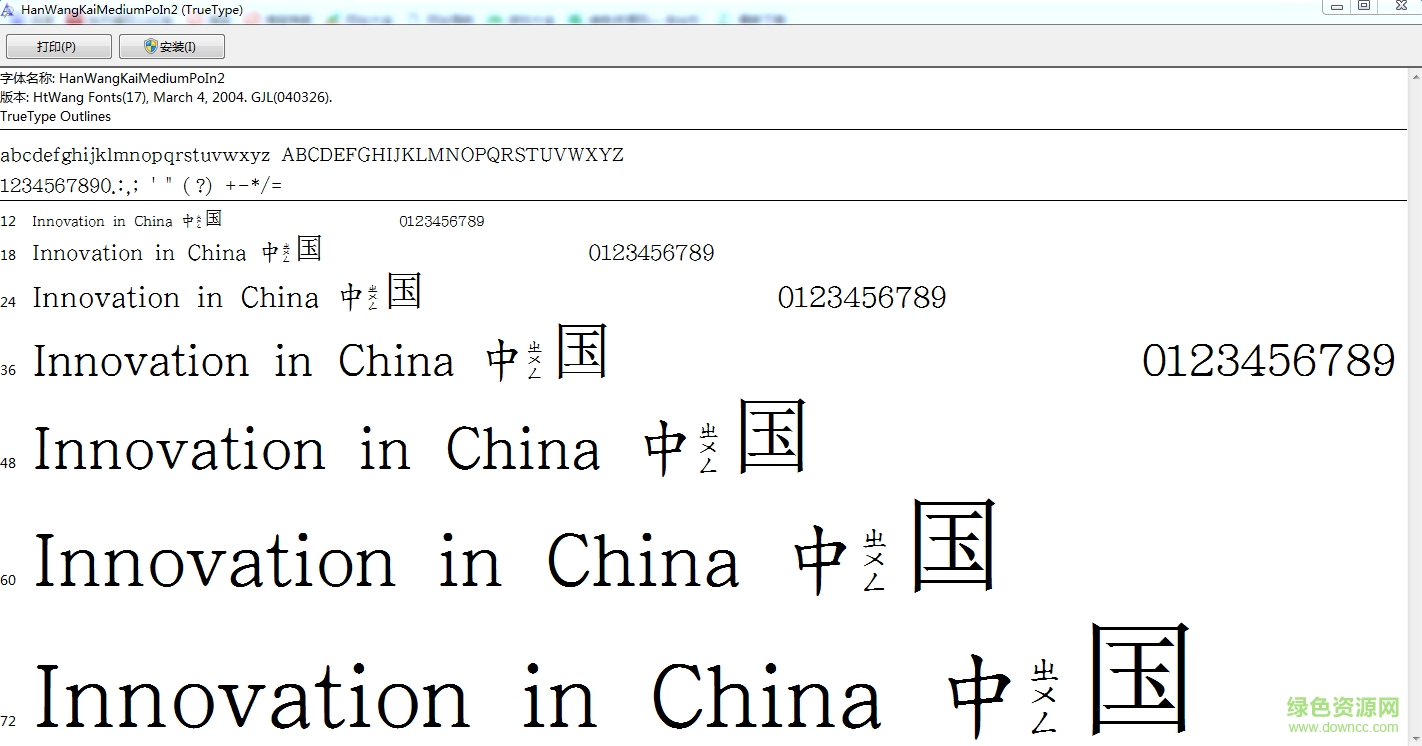
王漢宗中楷體破音二字體外形非常美觀。字體風(fēng)格和楷體類似,兼容不同的計(jì)算機(jī)系統(tǒng)環(huán)境。使用這款字體輸出的字體很大氣!深受廣大書(shū)法家和年輕人的喜愛(ài)!
王漢宗中楷體破音二是一款王漢宗類中楷字體破音二,字體效果比較正規(guī),破音二字體給人非常正式的感覺(jué),還有更多好看字體盡情期待,歡迎到綠色資源網(wǎng)下載體驗(yàn)!